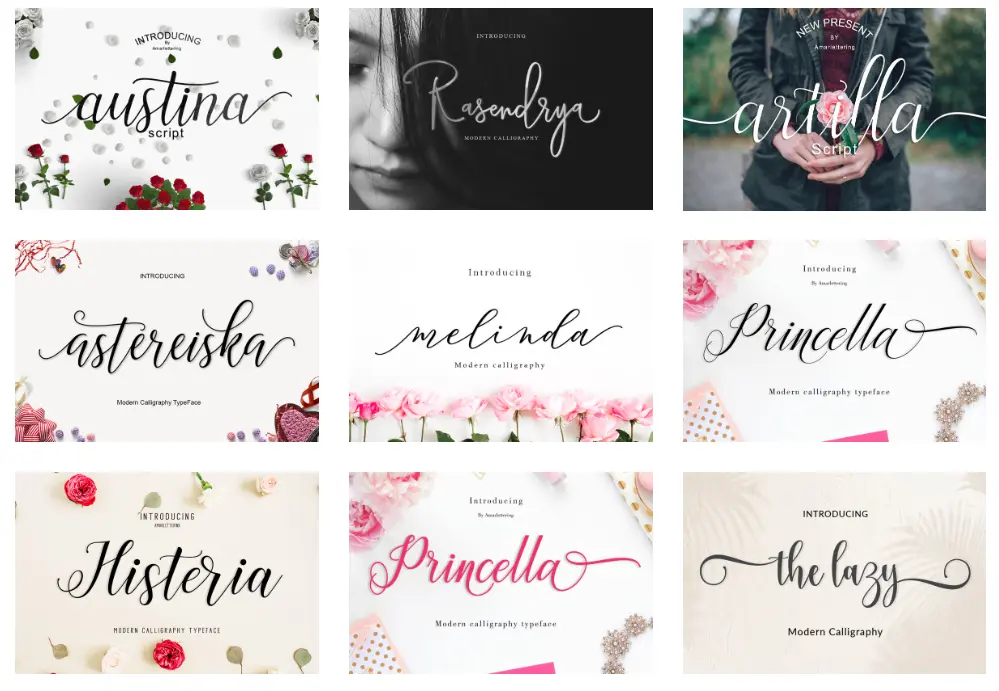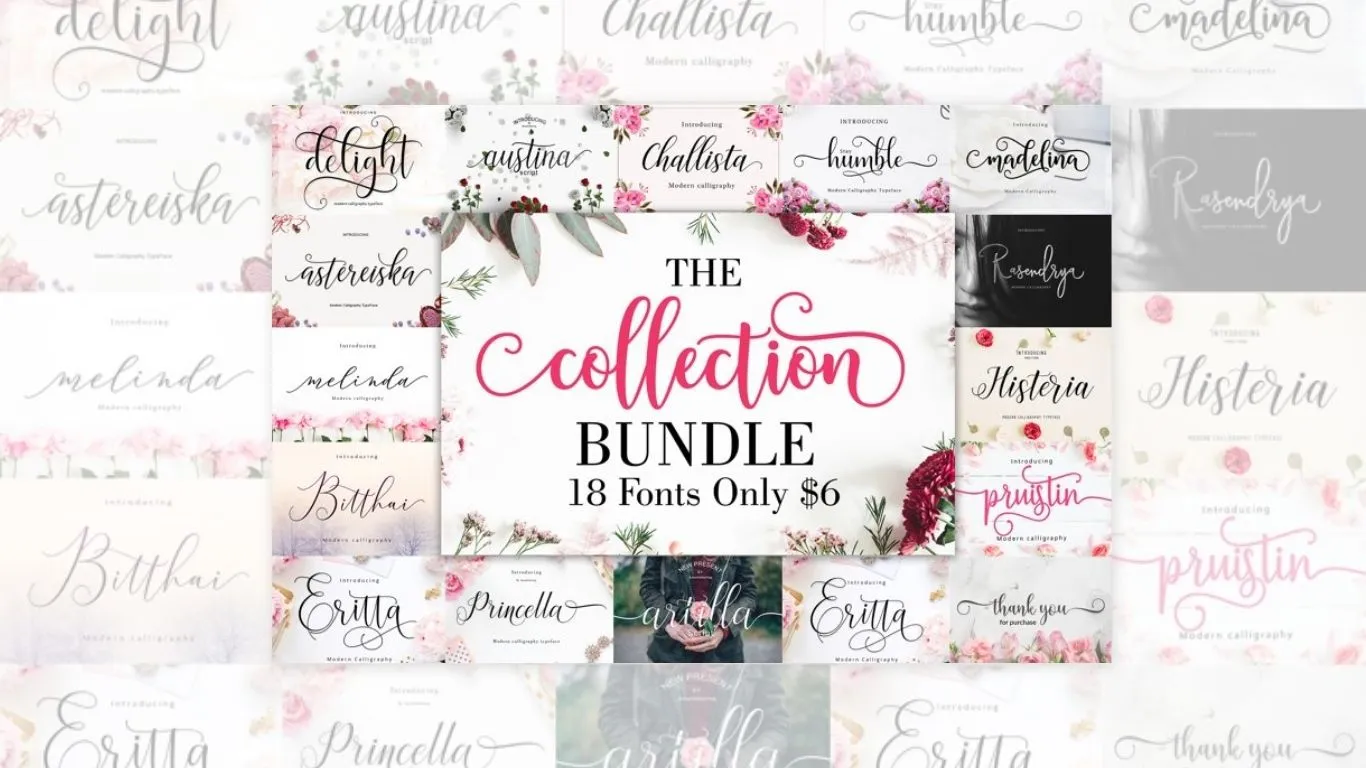
Font Bundles 每週免費字體包 The Collection Bundle
如果你平時有在留意字型資源,Font Bundles 的「每週免費字型」(Free Font of the Week) 絕對值得定期追蹤。這週推出的是 amarlettering 設計的「The Collection Bundle」,收錄 18 款手工繪製的現代手寫字體,風格優雅、用途廣泛,現在限時免費下載。如果你的字體庫還缺少幾套質感書法字體,這次絕對是好時機,趕緊去領起來!
字型包介紹
共收錄 18 款手工現代書法字體,每款都有各自的風格與用途,涵蓋 Script、Sans、Bold 等多種字型變化。以下是完整字體清單:
| 1 | Astereiska Script | 手寫 Script |
| 2 | Princella Script | 優雅書法 |
| 3 | Princella Bold | 粗體書法 |
| 4 | Princella Bold Slant | 粗體斜體 |
| 5 | Princella Slant | 斜體書法 |
| 6 | Princella Sans | 無襯線書法 |
| 7 | Madelina Script | 手寫 Script |
| 8 | Madelina Bold | 粗體手寫 |
| 9 | Madelina Bold Slant | 粗體斜體 |
| 10 | Madelina Slant | 斜體手寫 |
| 11 | Humble Script | 簡樸書法 |
| 12 | Humble Sans | 無襯線簡樸 |
| 13 | Melinda Script | 手寫 Script |
| 14 | Eritta Script Regular | 正規書法 |
| 15 | Eritta Script Bold | 粗體書法 |
| 16 | Eritta Script Slant | 斜體書法 |
| 17 | Kimberly Script | 優雅手寫 |
| 18 | Challista Script | 手寫 Script |